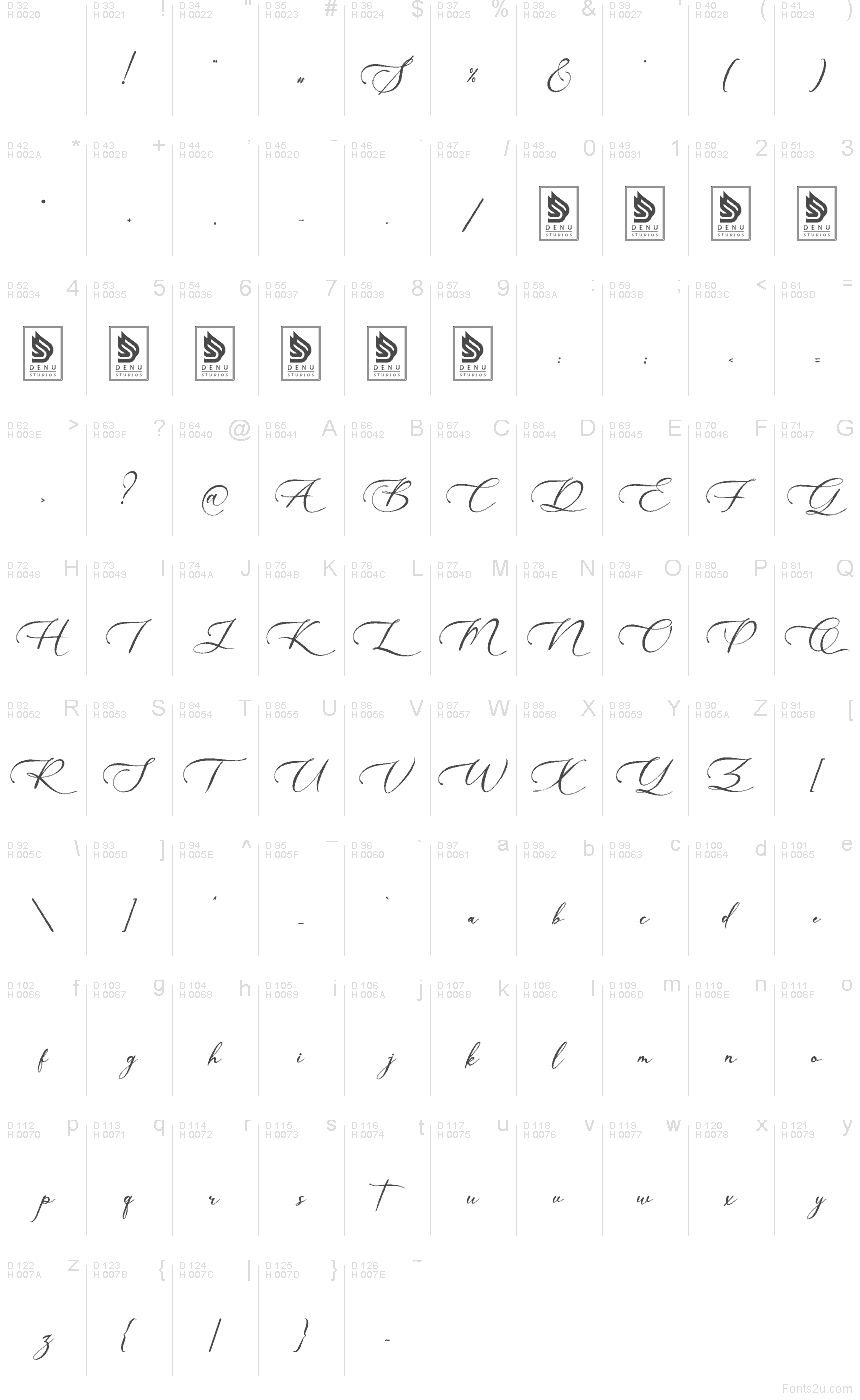
Willsyard de Denustudios es una tipografía caligráfica formal y gratuita, caracterizada por trazos largos y aireados que parecen escritos en un solo aliento elegante. Sus formas esbeltas, con una inclinación marcada y remates fluidos, le otorgan un aire refinado y ceremonial, manteniendo al mismo tiempo una suavidad que evita que se vea rígida.
Esta fuente gratuita encaja a la perfección en papelería de bodas, branding de joyería o perfumería, packaging de alta gama, portadas de revistas y menús de restaurantes que buscan un estilo distinguido. Es ideal para títulos, nombres en invitaciones y frases cortas, ya que sus florituras extendidas necesitan espacio para lucirse adecuadamente.